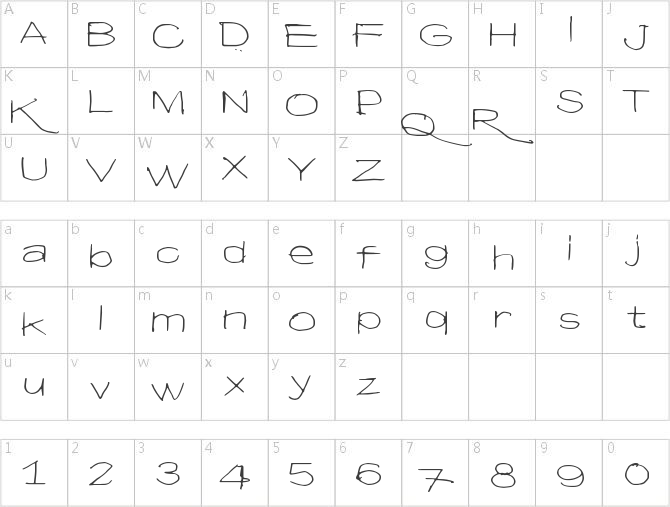
Hyva voittaa pahan 6-0
Hyva voittaa pahan 6-0介紹
Hyva voittaa pahan 6-0字體字庫是一款讓人賞心悅目、百看不厭的英文字體,適合各類廣告和產(chǎn)品包裝設(shè)計(jì)應(yīng)用,字體大小0.03MB,格式為ttf字體,上傳用戶是23KUN,作者/版權(quán)方為未知